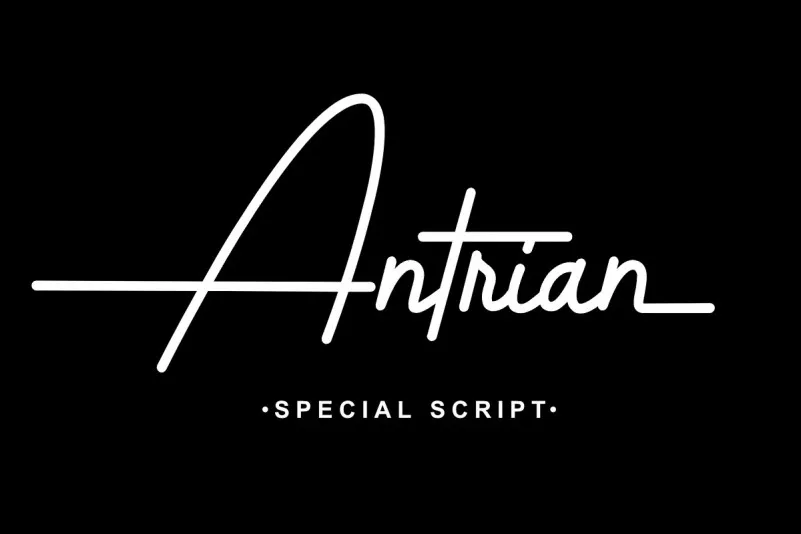
Antrian Font é uma elegante caligrafia monolínea para projetos digitais que buscam adicionar um toque refinado aos seus trabalhos. Esta fonte foi criada especialmente para designers que valorizam resultados perfeitos e resultados surpreendentes em suas criações de projeto. Com seu estilo casual e encantador, Antrian Font é a escolha ideal se você busca incorporar uma dose de elegância à sua próxima obra de arte digital. Desenvolvida pelo 99designs para os designers que buscam estilizar seus projetos com precisão e sofisticação, esta fonte oferece um formato script casual mas profissional, tornando-se uma excelente opção para criações que exigem um acabamento de alta qualidade. O Antrian Font é perfeito tanto para editoras digitais quanto para designers gráficos, garantindo que seu projeto seja reconhecido e apreciado por sua delicadeza inigualável.